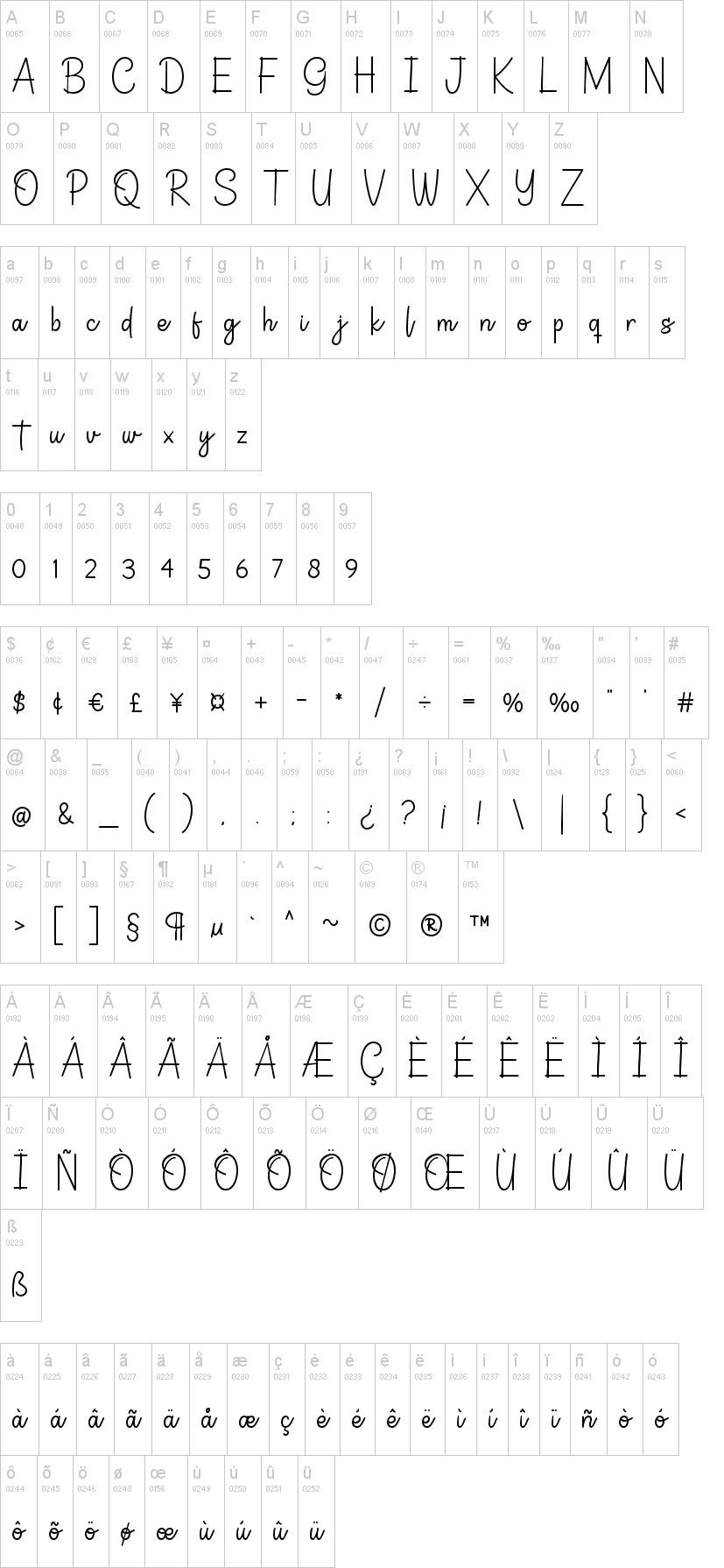
Germaint 是一种现代文本字体,它的特点是细节处理十分精致,采用了精细的线条和较大的字母间距,使字体更加清晰易读。它的字体风格精细而优雅,可以适用于各种文字类型,包括标题,正文,小标题,段落等。Germaint 字体具有良好的可读性,可以很好地显示文本,使文字更加清晰美观。内容介绍
Germaint是一款非常不错的手写艺术字体,具有很好的视觉感,适合于文化类的宣传设计、商业类品牌的广告和产品包装设计以及个性化文字排版等较多场景。